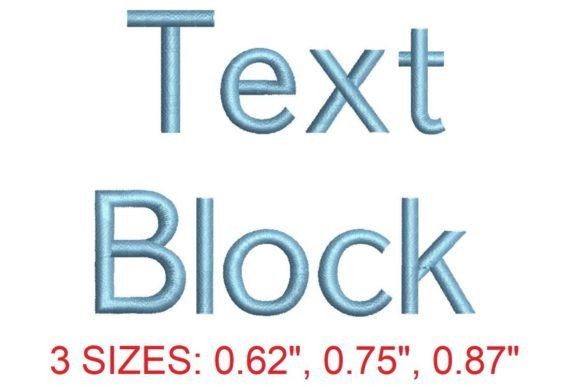
Text Block Embroidery Font
De 'Text Block Embroidery Font' is een adembenemend eenvoudig lettertype dat de kunst van de borduurkunst op een geheel nieuw niveau tillt. Met zijn minimalistische stijl en scherpe, duidelijke lijnen, biedt dit lettertype een ongeëvenaarde combinatie van elegantie en functionaliteit. Perfect voor zowel beginners als ervaren borduurders, past deze font naadloos in projecten waarin de nadruk wordt gelegd op zuiverheid en verfijning.
Bouwkwaliteit en technische details
Gemaakt met aandacht voor detail, is de 'Text Block Embroidery Font' ontworpen om perfect te functioneren op verschillende soorten textielen. Het lettertype ondersteunt een breed scala aan karakters, waaronder hoofdletters, kleine letters, cijfers en speciale tekens, wat het zeer flexibel maakt. De kwaliteit van de digitale bestanden is uitmuntend, met optimale stabiliteit en minimalisering van draadbreuk, wat leidt tot een soepele en efficiënte borduurervaring.
Voor wie is dit product het beste?
Vanwege zijn eenvoud en verscheidenheid, is de 'Text Block Embroidery Font' ideaal voor iedereen die houdt van minimalistisch design. Of je nu een ervaren borduurder bent of net begint, dit lettertype is perfect voor DIY-projecten, personalisatie van kleding, en zelfs voor het creëren van unieke cadeaus. Het is vooral geschikt voor mensen die op zoek zijn naar een lettertype dat zowel stijlvol als praktisch is, zonder overweldigend te zijn.
Zorg ervoor dat je de juiste draden en stabilisatiematerialen kiest om de fijnste details van dit lettertype optimaal weer te geven. Experimenteer ook met verschillende kleuren en textuurstoffen om een uniek effect te creëren dat perfect bij jouw project past.
Hoe het zich verhoudt tot de concurrentie
Tegenover andere borduurlettertypes zoals 'Sans Serif' of 'Script', staat de 'Text Block Embroidery Font' uit door zijn onmiskenbare eenvoud en moderne flair. Waar traditionele lettertypes soms te gedetailleerd kunnen zijn en daardoor moeilijk te borduren, biedt deze font een schone, eenvoudige lijn die gemakkelijk te werken is, zonder op te gaan in complexiteit. Dit maakt het niet alleen toegankelijker voor beginners, maar ook een favoriet onder ervaren borduurders die op zoek zijn naar een tijdloze en elegante oplossing.